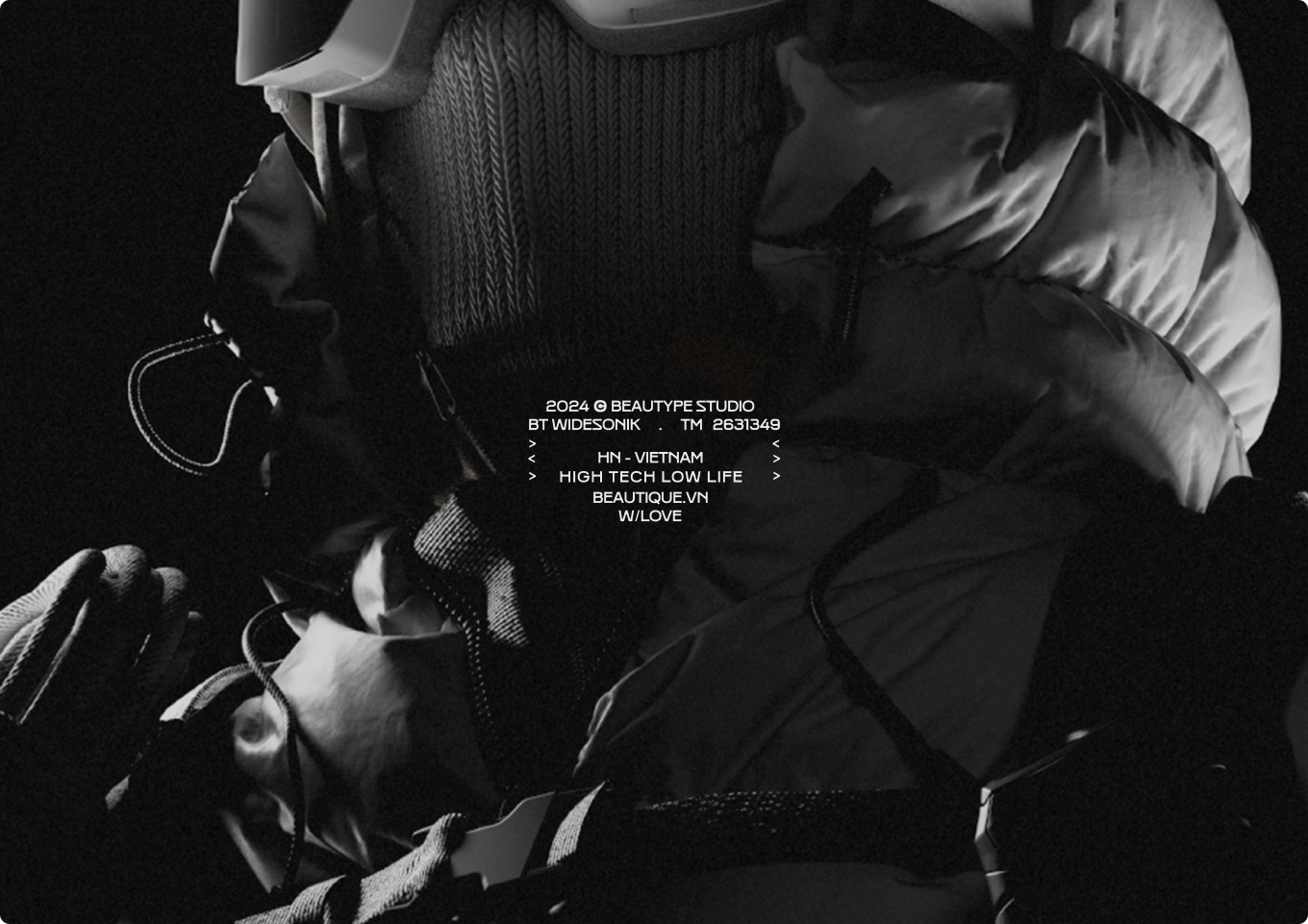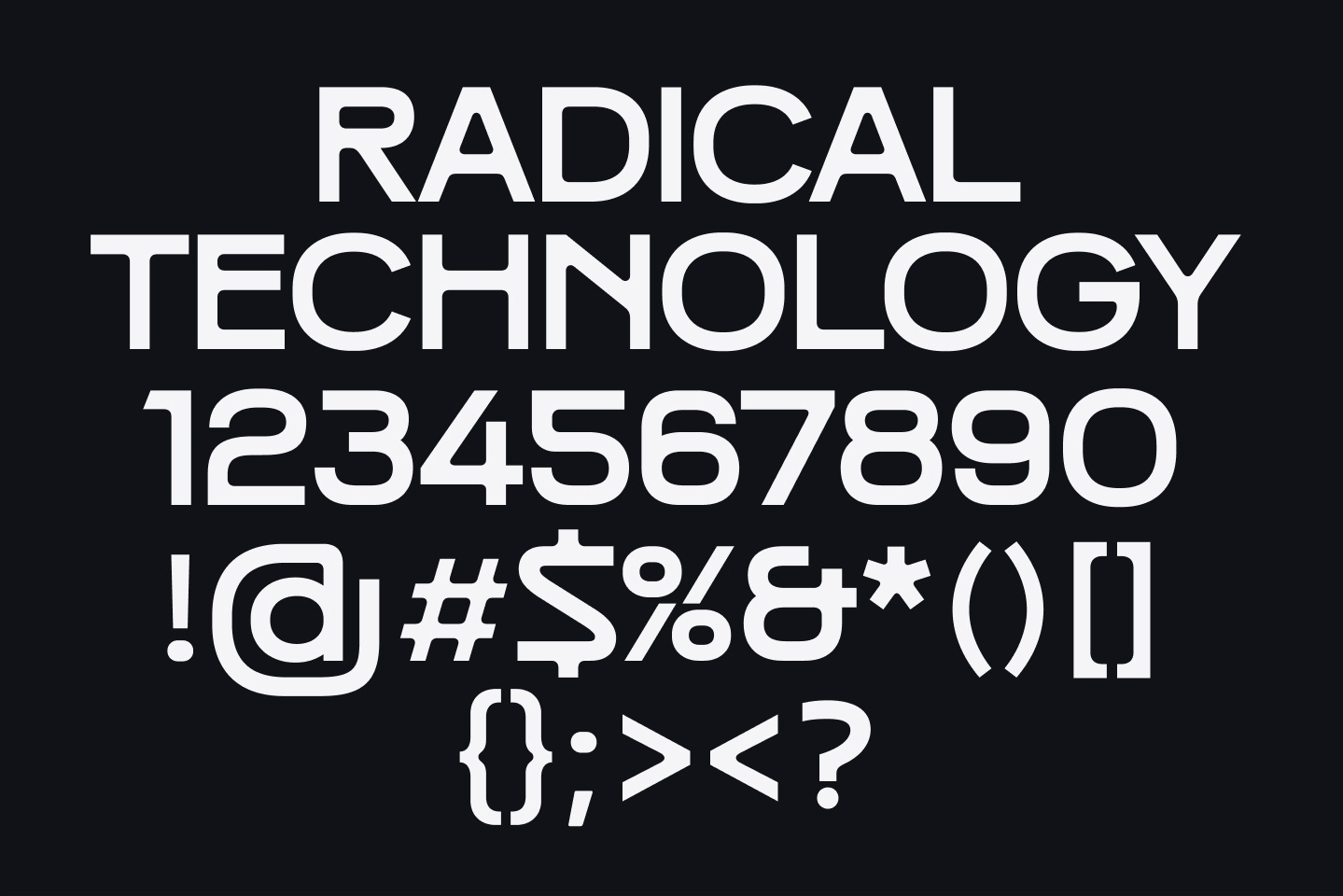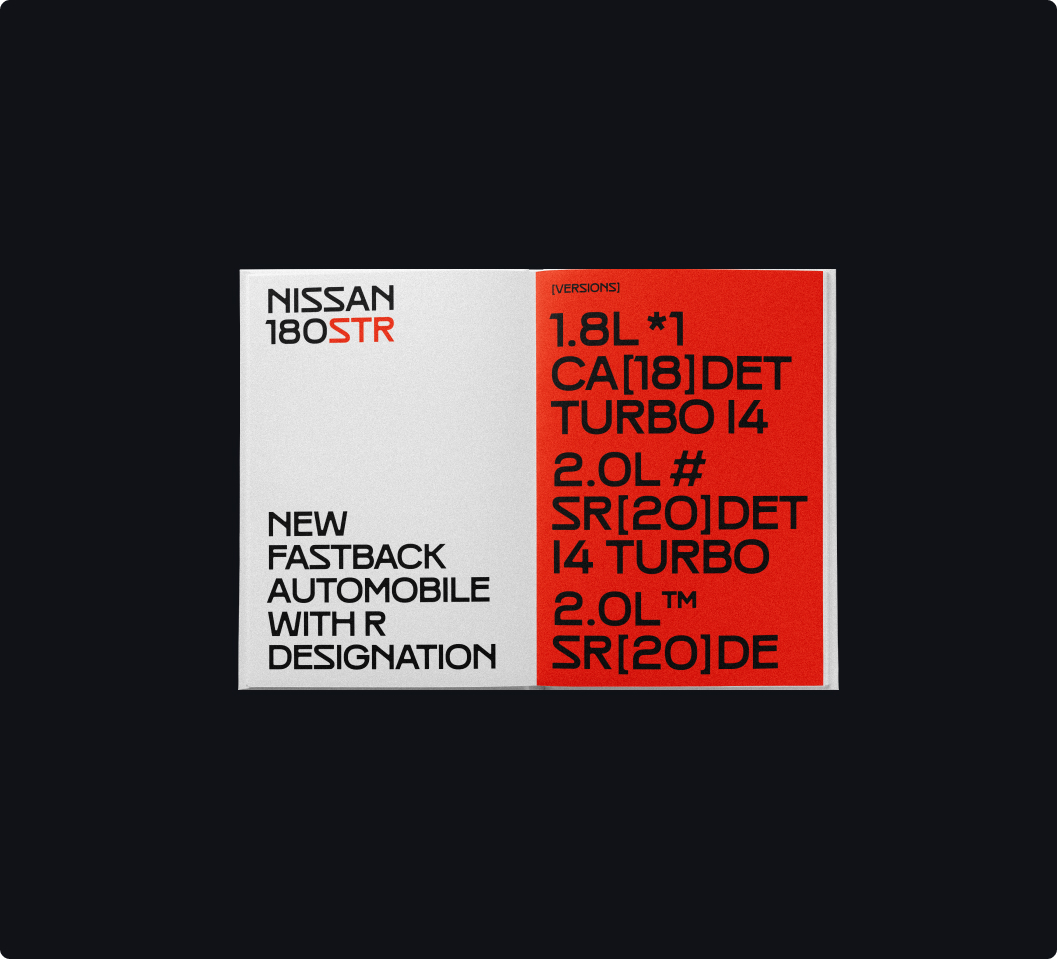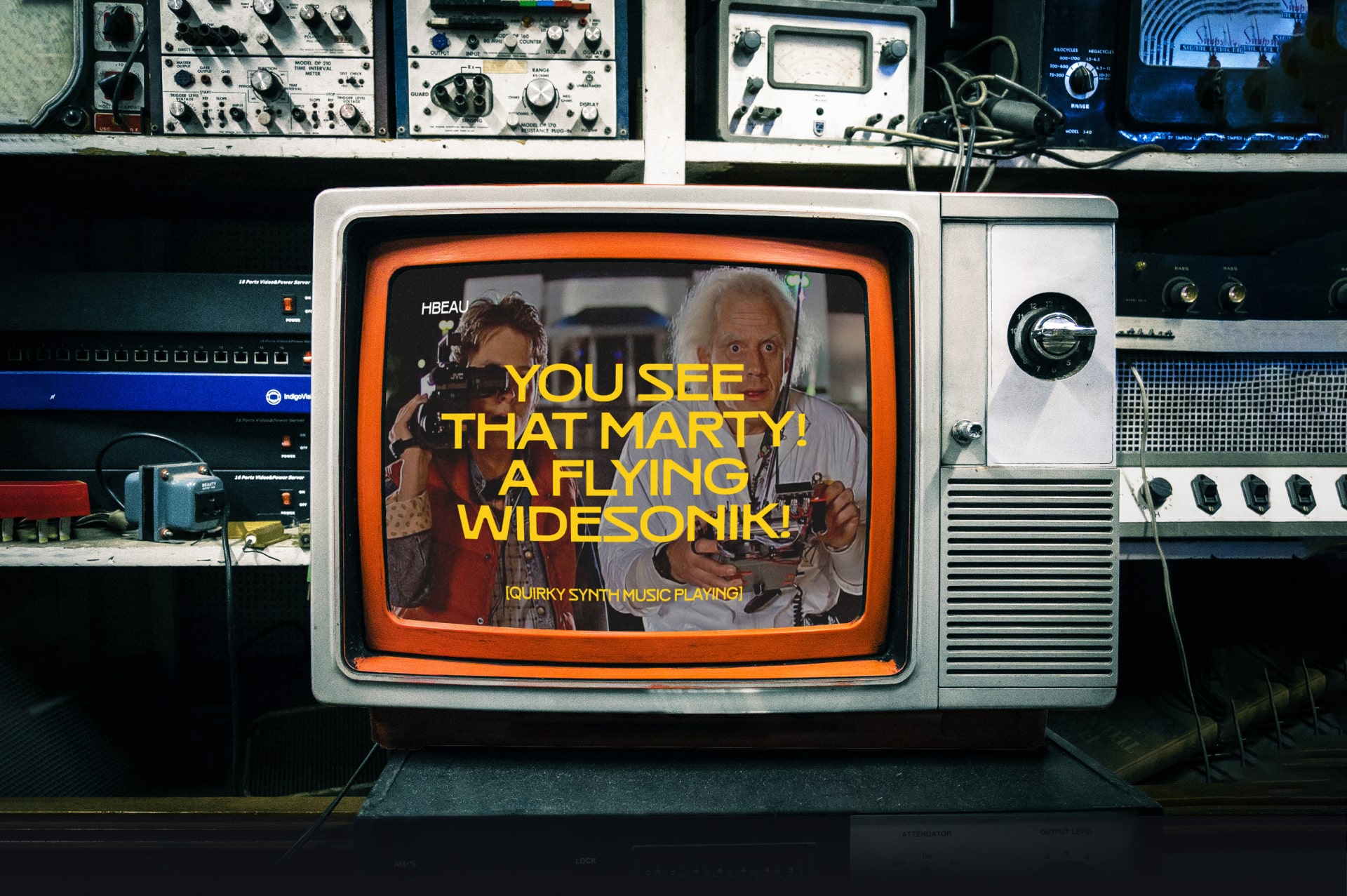
WIDE
SONIK
BT Widesonik là kiểu chữ được mở rộng bề ngang linh hoạt sử dụng trong nhiều lĩnh vực thiết kế
Dành cho thiết kế cần tính năng động & sức mạnh
Phông chữ này được khuyến khích sử dụng cho những thiết kế cần tính năng động, sức mạnh & nổi bật như thời trang công nghệ (techwear), vận tải tải trọng lớn, thiết kế đồ họa âm nhạc sôi động.
Một số lĩnh vực khác có thể thử nghiệm ví dụ như những thiết kế quảng cáo nghệ thuật đương đại, công nghệ sinh hóa,.. WIDESONIK là một kiểu chữ vô cùng cá tính và linh hoạt phù hợp với nhiều mục đích thiết kế khác nhau.
INTO THE
NIGHT
BT Widesonik du hành thời gian bằng con chữ & thổi hồn cho thiết kế đậm tính tương lai
GỢI Ý SỬ DỤNG
Tiếng gọi cho một kỷ nguyên hiện đại
Widesonik là phông chữ linh hoạt dễ dàng ứng dụng được vào những thiết kế mang hơi hướng của một kỷ nguyên hiện đại hóa. Ví như một kẻ du hành thời gian Time Traveler đi từ những thiết kế retro của thập niên 80s, cho tới hiện tại là những gì tương lai nhất của một thế giới kết nối liên tục và rộng mở.
BT WIDESONIK
Character Set
Basic Latin
Vietnamese
Punctuation, Numerals, Currencies
EXPERIENCE THE “TIME TRAVER”
TYPEFACE
BT WIDESONIK
BY BEAUTYPE STUDIO™